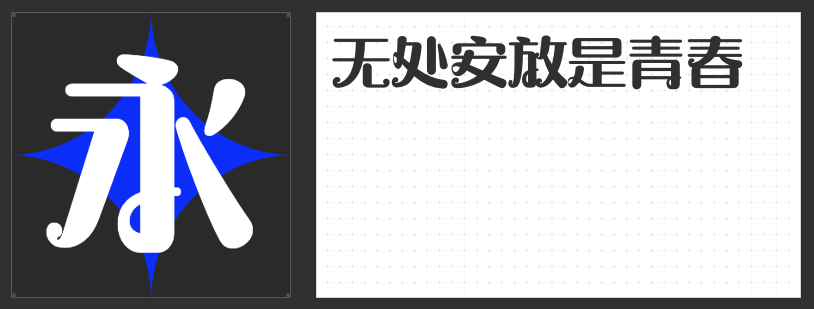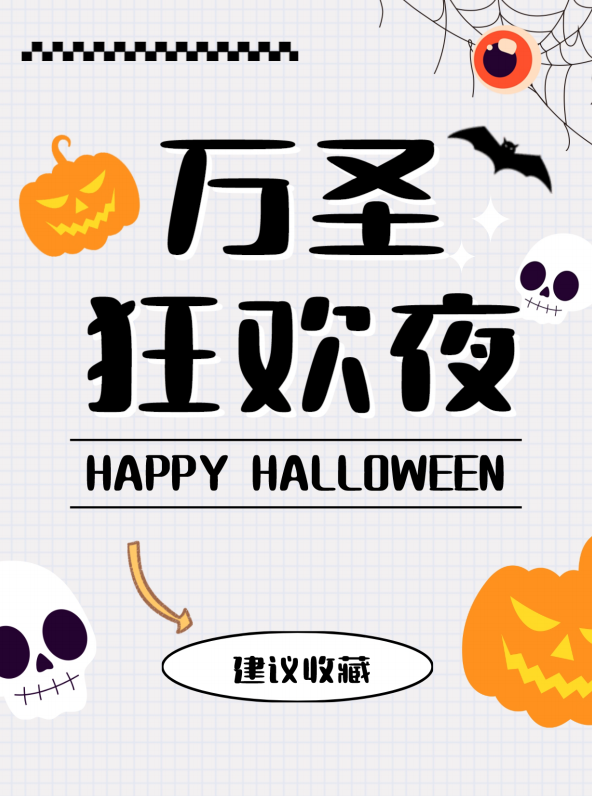
打造独特品牌视觉的四款创意字体,快来试试吧!
在Logo设计中,字体选择至关重要,它不仅影响着品牌的整体形象,还能传达出品牌的独特气质。今天,为大家推荐四款适用于Logo设计的精选字体,它们各具特色,能够满足不同品牌风格的需求。
一、励字圆梦简 中黑
励字圆梦简 中黑以其圆润柔和的笔画和简洁明了的设计,成为Logo设计中的佼佼者。这款字体采用直线笔画,以竖折笔画代替部分弧线,使得整体字形更加简洁有力。笔画起笔、收笔和转折处的圆弧风格,赋予了字体自然的流动感。中宫松散、外圆内方的设计,使得字体在视觉上更加舒适,适合打造现代简约风格的Logo。
高手庆科巧克力 大圆字体以其圆润饱满的笔画和整体平衡的设计,赢得了众多设计师的喜爱。这款字体宽扁适中,中宫略大,布白均匀,使得整体字形更加稳定和谐。笔画设计简洁无过多装饰,横细竖粗,笔形圆润,弧度饱满,展现出一种温馨而亲切的气质。无论是中文还是西文符号,都保持了高度的统一性和协调性,非常适合打造温馨、亲和的品牌形象。
高手庆科数码体 大黑字体以其独特的像素风格,为Logo设计带来了全新的视觉体验。这款字体笔画设计横细竖粗,用错位像素代替部分笔画,使得整体字形充满了现代感和装饰性。同时,笔画中的缺失像素点被巧妙地填补,使得字体更加完整和美观。无论是中文还是西文符号,都保持了高度的统一性和趣味性,非常适合打造科技、时尚的品牌形象。
四、励字摩登圆简
励字摩登圆简字体以其富有装饰意趣的设计,成为Logo设计中的多面手。这款字体可复古可新潮,可严谨又可浪漫,甚至能够完美融入儿童风画面。其多变的风格使得它适用于多种风格的包装、书、报、杂志、电商等装饰用字。在Logo设计中,励字摩登圆简能够轻松打造出独特而富有吸引力的品牌形象。